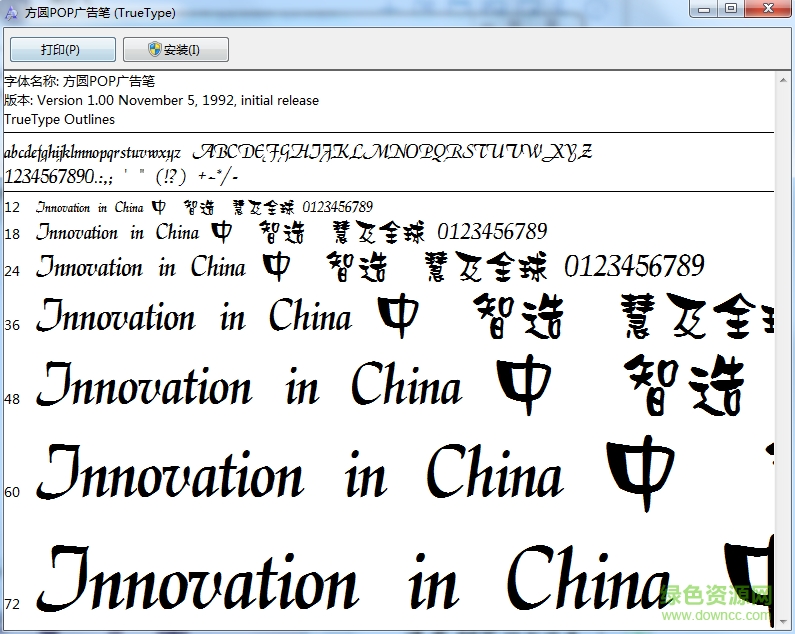
方圓POP廣告筆
方圓POP廣告筆是一款繁體輸入的pop字體,在POP設(shè)計(jì)中常有用到,字跡簡潔獨(dú)特,充滿個(gè)性韻味,喜歡的朋友就來綠色資源網(wǎng)免費(fèi)下載吧!
方圓POP廣告筆字體介紹
方圓POP廣告筆字體是一款用于POP設(shè)計(jì)方面的字體,整體字體筆畫粗細(xì)不均,字體具有清晰大方的風(fēng)格,字形具有藝術(shù)特點(diǎn),本作品適用于創(chuàng)意設(shè)計(jì)字體、藝術(shù)設(shè)計(jì)字體、POP設(shè)計(jì)字體、方圓設(shè)計(jì)字體。
方圓POP廣告筆是一款可用來設(shè)計(jì)海報(bào)雜志、廣告創(chuàng)意等的卡通字體,是一款繁體字體,部分字和標(biāo)點(diǎn)不夠完整,商用請(qǐng)到相關(guān)網(wǎng)站授權(quán)!